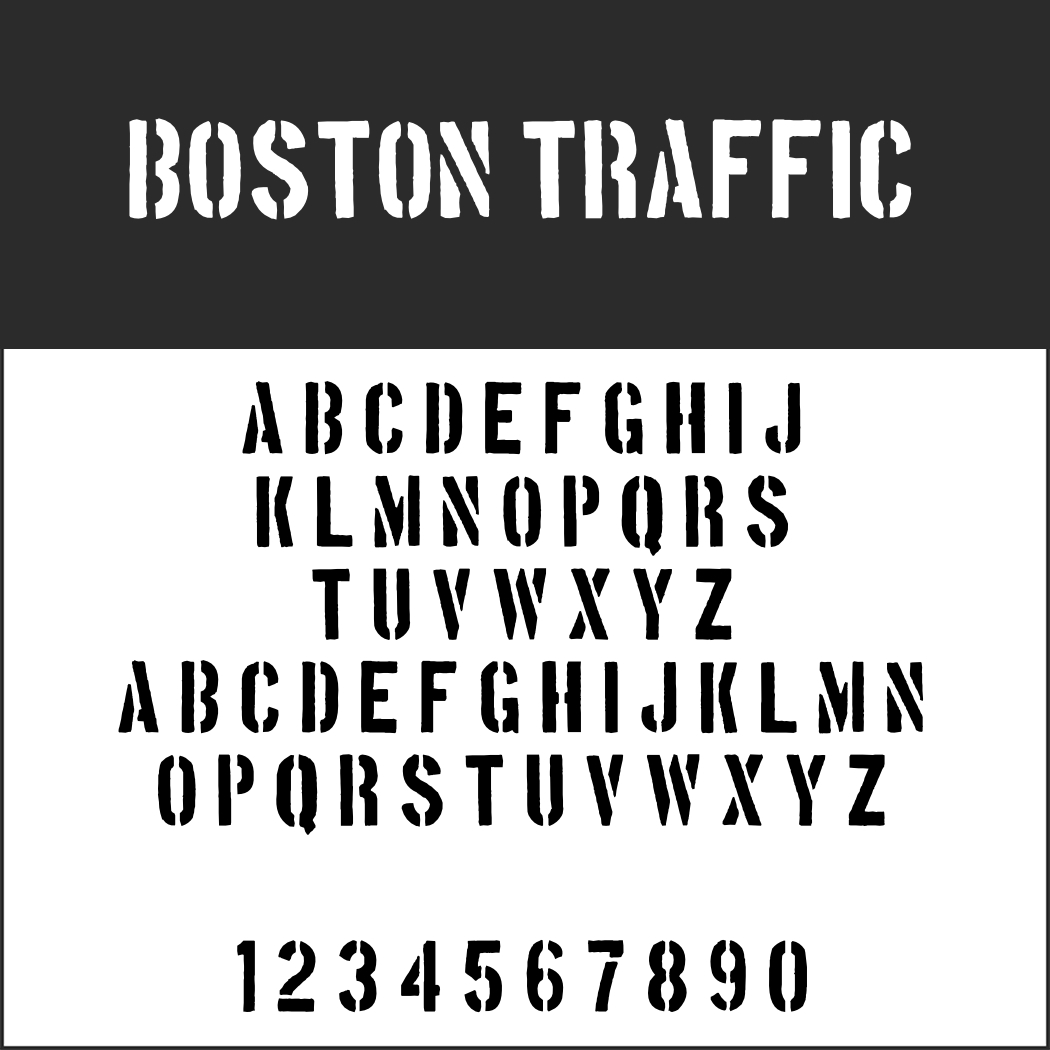
Ganz oft handelt es sich bei einer Militär Schriftart um einen Stencil-Font, zu dem Sie eine Auswahl unter Schriftart Schablone finden. Es gibt aber auch einige andere, die ähnliche Assoziationen hervorrufen und vorwiegend „männliche Themen“ illustrieren.
Dabei beziehen sich diese Militär Fonts nicht generell auf eine Armee, sondern mehr oder weniger direkt auf die US Army. Der Grund liegt vermutlich darin, dass keine andere Armee so häufig eine (positive) Rolle in Hollywood-Filmen spielt.
Die Bundeswehr führt in dieser Hinsicht ein Schattendasein. Ihre offizielle Schriftart ist die Frutiger. Mehr dazu finden Sie auf der Seite des Verteidigungsministeriums.
Militär SchriftartArmalite Rifle
Der Font Armalite Rifle trägt nicht nur den Namen „Schnellfeuerwaffe“, sondern sieht auch so aus, als wäre er einer zum Opfer gefallen.
• Besonderheit: keine Kleinbuchstaben, keine deutschen Sonderzeichen
• Design: Vic Fieger
Black Ops One
Für die halbgeometrische Schriftart dienten militärische Schablonenschriften als Vorlage.
Militär SchriftartBoston Traffic
Diese Schablonenschrift ist relativ schmal und eignet sich daher besonders gut für die Beschiftung von Schildern.
• Besonderheit: keine Kleinbuchstaben, keine deutschen Sonderzeichen
• Design: Vic Fieger
Call of Ops Duty
Die britische Designerin, die auch Computerspiele entwickelt, ließ sich für diesen Font von den Games Call of Duty und Impact inspirieren.
Militär SchriftartDream Orphanage
Die Wiederbelebung des Fonts Dream Orphans aus den 1990er Jahren bietet mit sieben Schriftschnitten vielfältige Einsatzmöglichkeiten.
Militär SchriftartFragile Bombers
Fragile Bombers passt hervorragend zu (militärischen) Science-Fiction-Themen.
Interplanetary Crap
Diese Stencilschrift sieht mitgenommen aus und erweckt den Eindruck, der beschriftete Gegenstand wäre in gefährlichem Einsatz gewesen.
Militär SchriftartLintsec
Eine weitere Schablonenschrift, deren große Aussparungen das Charakteristische ausmachen.
Nasalization
Sowohl Name als auch Stil des ultramodernen Fonts weisen auf ein Logo der NASA aus dem Jahr 1975 hin.
Militär SchriftartPirulen
Futuristisch und streng präsentiert sich dieser Militär- und Science-Fiction-Font.
Quantico
Der Designer ließ sich für Quantico von militärischen Schriften und alten Bierverpackungen inspirieren.
Militär SchriftartRadio Stars
Radio Stars ist in allererster Linie für aufmerksamkeitsstarke Schlagzeilen konzipiert.
Militär SchriftartRexlia
Die Vorlage für diese moderne Schrift im Industrie-Stil stammt von Verpackungen neuester Militärausrüstung.
Rothwell
Auch Rothwell ist von echten Militärschriften beeinflusst und wirkt zudem leicht futuristisch.
Spectrashell
Bewusst plakativ gibt sich Spectrashell, das sich vor allem für Schlagzeilen eignet.